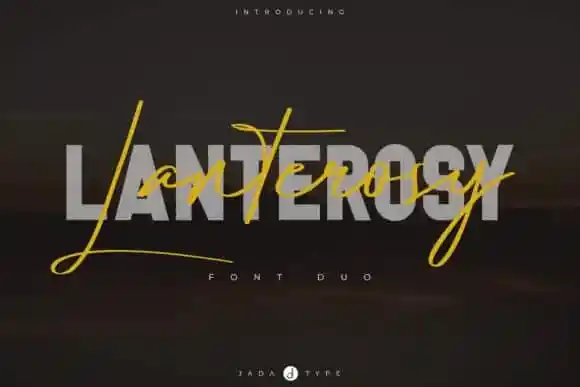
Lanterosy Font Duo – Download Grátis
Lanterosy Font Duo é uma dupla de tipografia moderna que combina letra curva com sans serif. Lanterosy Script transmite elegância e suavidade, enquanto Lanterosy Sans Serif apresenta firmeza e assertividade. Com letras estilizadas que se complementam perfeitamente para qualquer aplicação de design gráfico, esta fonte é ideal tanto para títulos quanto para logotipos. Lanterosy (Script & Sans) inclui um conjunto completo de letras do alfabeto inglês e suporta várias línguas, tornando-a versátil em diferentes contextos linguísticos. É fácil instalar na maioria dos programas de design gráfico, como o Adobe Family, Affinity Design e mais, permitindo que você trabalhe com liberdade dentro do seu processo criativo.